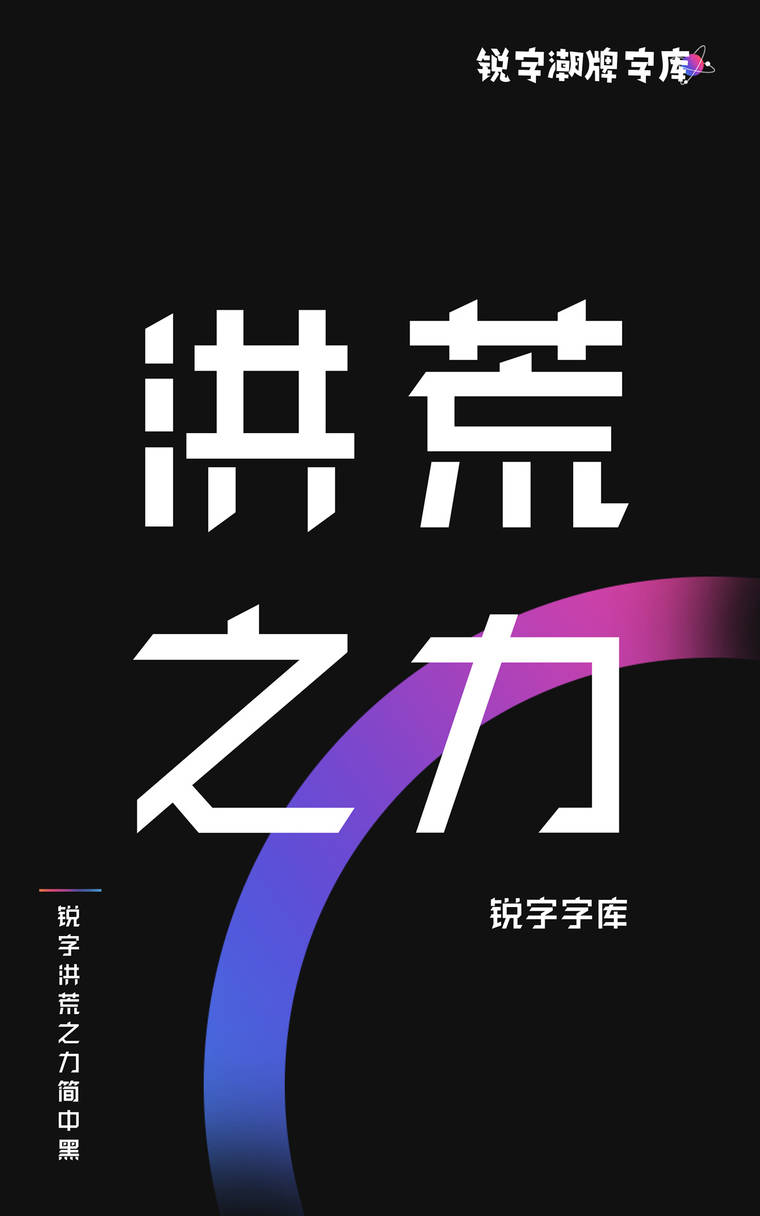
锐字洪荒之力简 中黑
锐字洪荒之力简 中黑字体介绍
锐字洪荒之力简 中黑,是锐字系列品牌字库旗下的一款字体。锐字潮牌字库拥有本字体独家版权,并提供锐字洪荒之力简 中黑的官方免费下载服务。
字体特征:锐字洪荒之力的设计灵感来源于网络热词“洪荒之力”,旨在体现原始、粗野的生命活力感。字形上棱角分明、刚健有力,共有4款字重,可满足不同的需求。